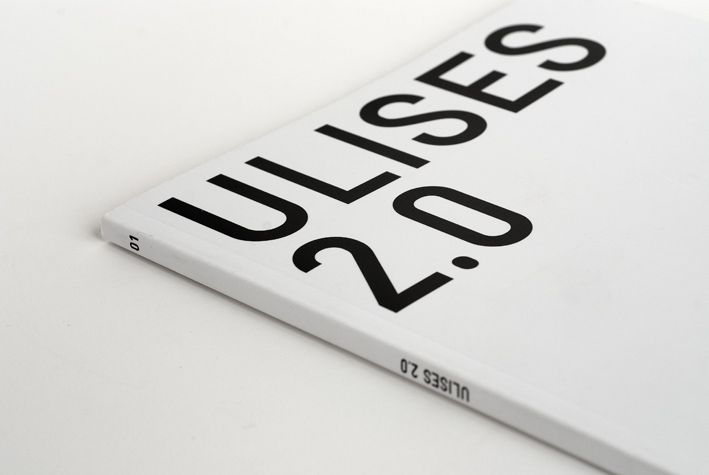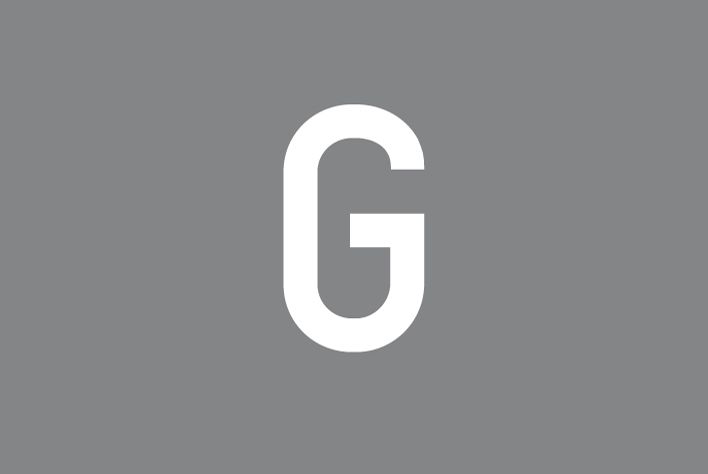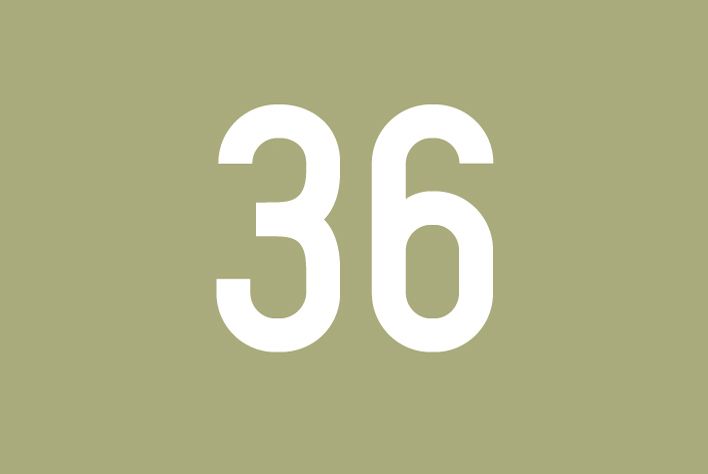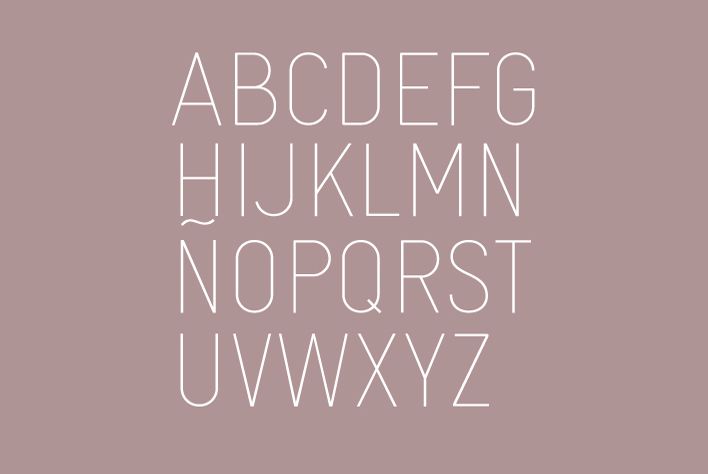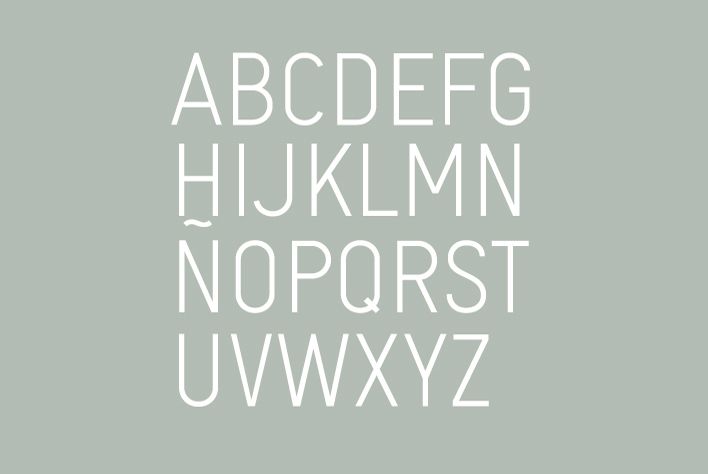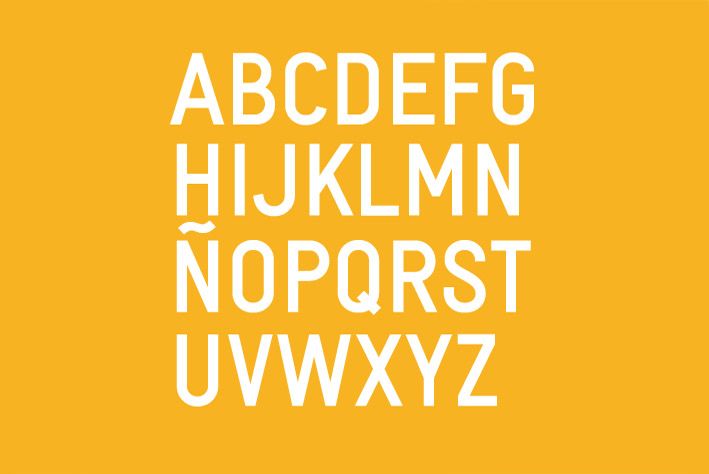
Esta es mi primer y único, hasta el momento, trabajo tipográfico, pero espero que haya muchos más a partir de ahora.
Es una tipografía creada a partir del logotipo de la empresa, en sus versiones bold, light y thin.
Un trabajo arduo, pero muy, muy gratificante.
yep, nice nice typography, how much potential!
love it !! very clean and ... I like it !! : D
The S bold is perfect!
it reminds me of one of my favorite types, the DIN but as condensed. good job
For clear and direct headlines it is perfect.